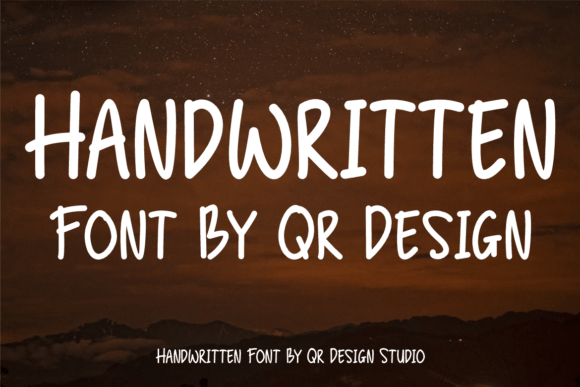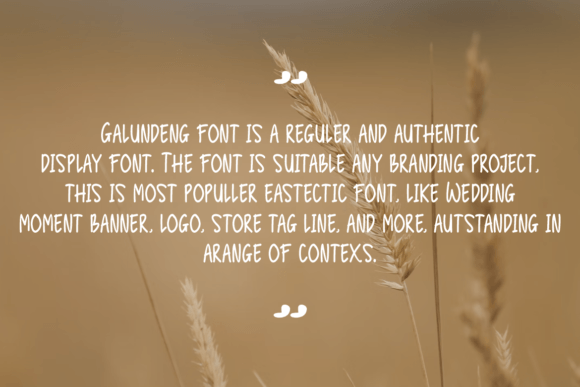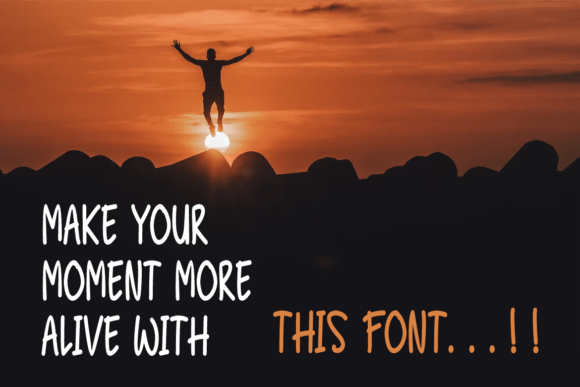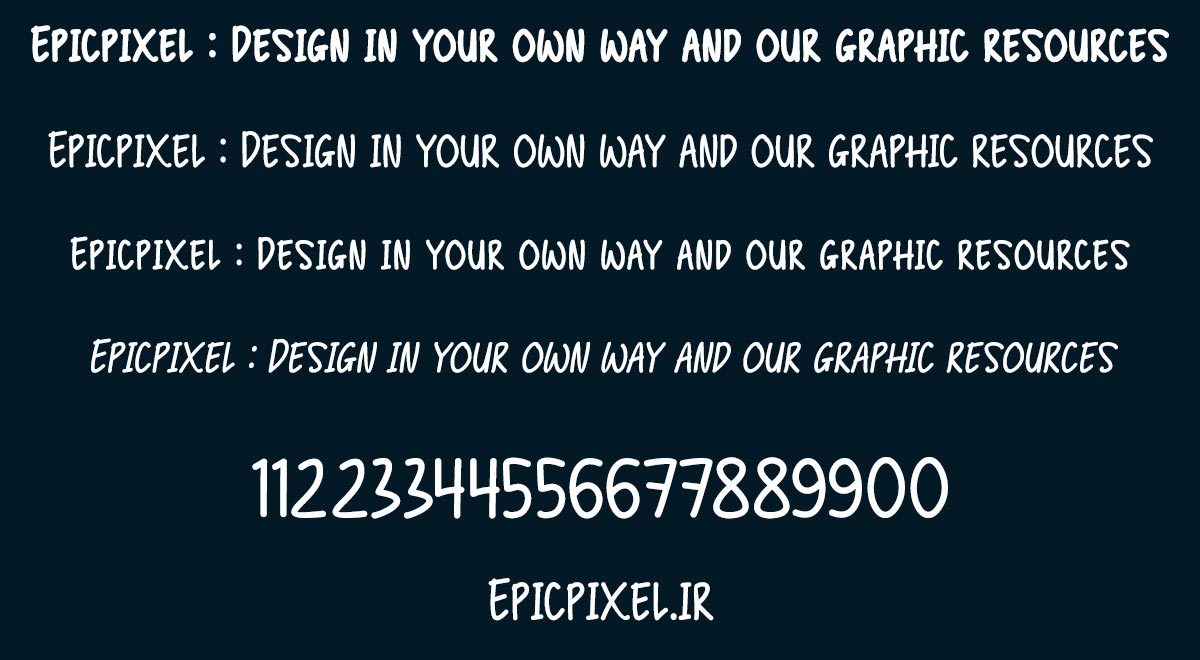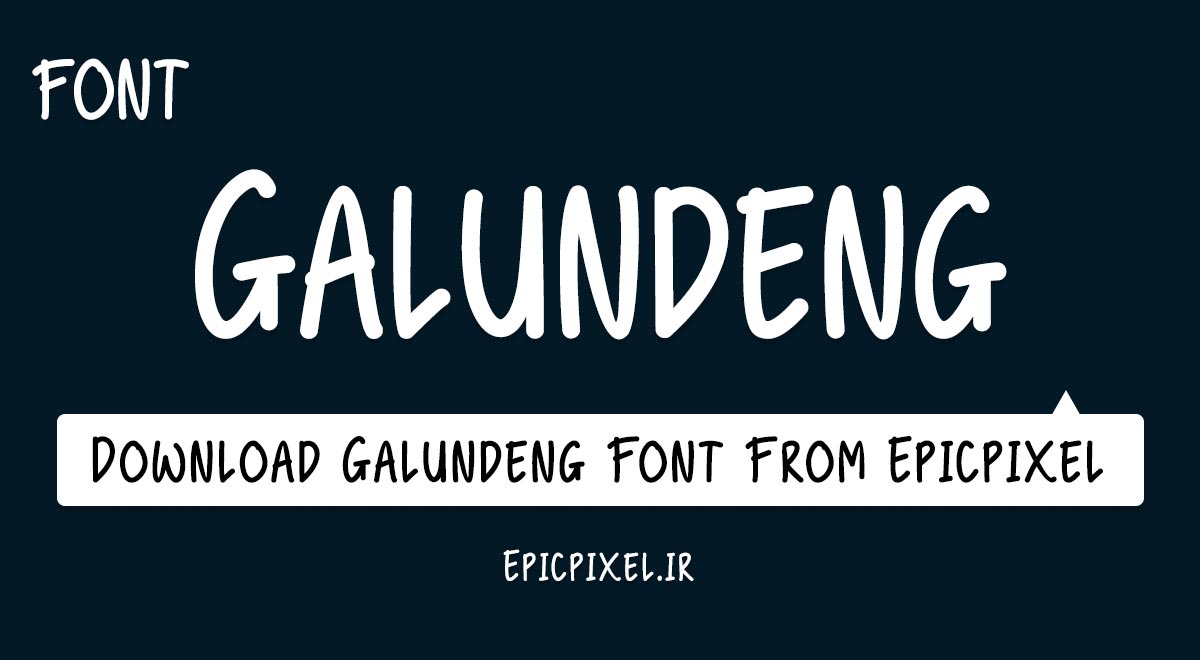
فونت Galundeng انگلیسی
دانلود فونت Galundeng انگلیسی Font گالاندگ |
| ⭐ مجموعه فونت | دانلود فونت انگلیسی گالاندگ Font Galundeng |
| ⭐ توضیحات | Galundeng Font یک فونت نمایشگر برجسته و معتبر است. این فونت برای هر پروژه برندسازی مانند لوگو، غذا و بسیاری موارد دیگر مناسب است. برجسته در طیف گسترده ای از زمینه ها. |